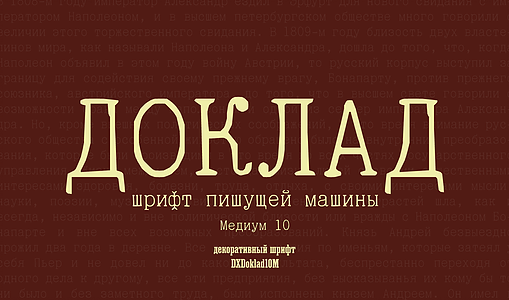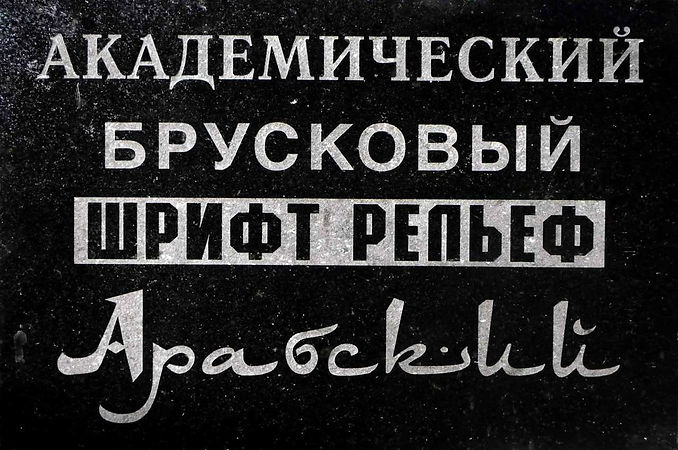
Брусковые шрифты. (Смирнов, в.Тоотс)
Брусковые шрифты — собирательное название шрифтов c мощными засечками прямоугольной формы без скруглений или с небольшим скруглением в местах присоединения к основным штрихам, имеют малый контраст между основными и соединительными штрихами или полное отсутствие контраста, крупное очко строчных знаков. Первые подобные шрифты появились в Англии в начале XIX в. Шрифты этого типа занимают ведущее место по шкале читабельности и идеально подходят для набора длинных текстов, так как имеют очень слабый контраст. Однако страница, набранная этим шрифтом, выглядит значительно «темнее» страницы, набранной обычной гарнитурой, поскольку штрихи брускового типа плотнее и более единообразны по толщине.
Брусковые
шрифты близкие к антикве (первая
половина 19в.) – (Кларендон)Очень маленький
контраст, вертикальная форма овалов. У
таких шрифтов засечки присоединяются
к основным штрихам со скруглением.
Первый шрифт под названием Clarendon был
создан в Лондоне в 1845 г.
Шрифты близкие к гротеску (вторая половина 20 в.), напоминающие венецианскую Гуманистическую антикву старого стиля, но малоконтрастные и с мощными прямоугольными засечками, обычно разрабатываюится в пару к гротескным шрифтам, в названии как правило используеься слово serif. Примеры: PMN Caecilia, Joanna, ITC Officina Serif.
Старые гротески, их разновидности. (Смирнов, в.Тоотс)
Старые гротески (первая половина
19в.) — это одноширинные закрытые или
полузакрытые шрифты без засечек с
эллиптическими овалами, впервые
появившиеся в Англии в 1816 г. Их знаки
отличаются заметным контрастом между
основными и соединительными штрихами.
Отличаются некоторой неправильностью
формы, имеют и закрытые и открытые
форсмы, в названии обычно присутсвуют
слова Gothic или Grotesk.
Примеры: Akzidenz Grotesk, Bell Gothic, Franklin Gothic, News Gothic, Trade Gothic, Venus.
Новые гротески. Ленточная антиква. (Смирнов, в.Тоотс)
Новые гротески(середина 20 в.)
АНТИ́КВА-ГРОТЕ́СК— разновидность шрифта, разработанного на основе антиквы, но имеющего минимальное различие, либо одинаковую толщину вертикальных и горизонтальных штрихов, как у гротеска, короткие закругления или небольшие утолщения на концах стоек вместо засечек антиквы. Эта форма очень древняя, ее образцы встречаются в древнегреческой и римской эпиграфике (посвящениях, надписях на художественных памятниках). Новая, упрощенная форма этого типа — ленточная антиква, отличающаяся от классической полным отсутствием засечек.
Эволюция книги. История книгопечатания. (Королькова, Живая типографика)
Типы шрифтов. Разделение их на категории с точки зрения дизайна и назначения. (Королькова, Живая типографика)
Классификация шрифтов по ГОСТу.
(Смирнов, Королькова,
Живая типографика)Историческая классификация шрифтов. (Смирнов, Королькова, Живая типографика)
Понятие гарнитуры и начертаний. Состав шрифта. (Королькова, Живая типографика, стр.114)
Гарнитура — совокупность типографского наборного материала, различного по начертанию и размерам, но имеющего одинаковый характер рисунка.
НАЧЕРТАНИЕ ШРИФТА — графическая разновидность шрифта в пределах одной гарнитуры, различаемая по плотности (ширине) очка (нормальное, узкое, широкое Н. ш.), по постановке (наклону) очка (прямое, курсивное, наклонное Н. ш.), по насыщенности (жирности) очка (светлое, полужирное, жирное Н. ш.).
Типометрическая система. Типографский пункт, его связь с другими единицами. (Королькова, Живая типографика, стр.90)
Размер
типографского пункта.Существует две
системы измерения шрифтов — так
называемая, французская система (система
Дидо), созданная в Париже в 1785 г.
и
принятая в Европе (Германия, Франция и
др.) и позднее в России (СССР), а также
англо-американская система, где основной
единицей является пика (пайка, от англ. pica).
В любом случае основной единицей
измерения является типографский пункт.
В системе Дидо 1 п. = 0,3759 мм (при расчетах
эту величину всегда округляют до значения
0,376 мм), а в англо-американской системе —
0,3527 мм (1/72 дюйма).
Параметры шрифта: кегль, интерлиньяж, трекинг, кернинг. (Королькова, Живая типографика, стр.90; распечатка с терминами)
Кегль (от нем. kegel) —
переводится как размер высоты буквы,
включая нижние и верхние выносные
элементы у этой буквы или знака. В ручном
наборе высокого способа печати кегль
измеряли через высоту литерной площадки,
на которой расположена буква или знак.
В линотипном наборе кегль измеряли
через расстояние между задней и передней
стенками строки. Кегль измеряется в
типографских пунктах. Высота литерной
площадки включает в себя нижнее заплечико,
высоту самой буквы (знака) и высоту
верхнего заплечика.
Ке́рнинг (англ. kerning) при наборе текста — избирательное изменение интервала между буквами в зависимости от их формы.
Технология кернинга включает подбор межбуквенных интервалов для конкретных пар букв с целью улучшения внешнего вида и удобочитаемости текста. Такой избирательный подбор позволяет компенсировать неравномерности визуальной плотности текста, получаемой при использовании стандартных апрошей для каждой буквы. Значение кернинга в программах вёрстки устанавливается в процентах от ширины символа пробела используемого шрифта; оно может быть как положительным (когда знаки раздвигаются), так и отрицательным в случаях, когда знаки приближаются друг к другу.